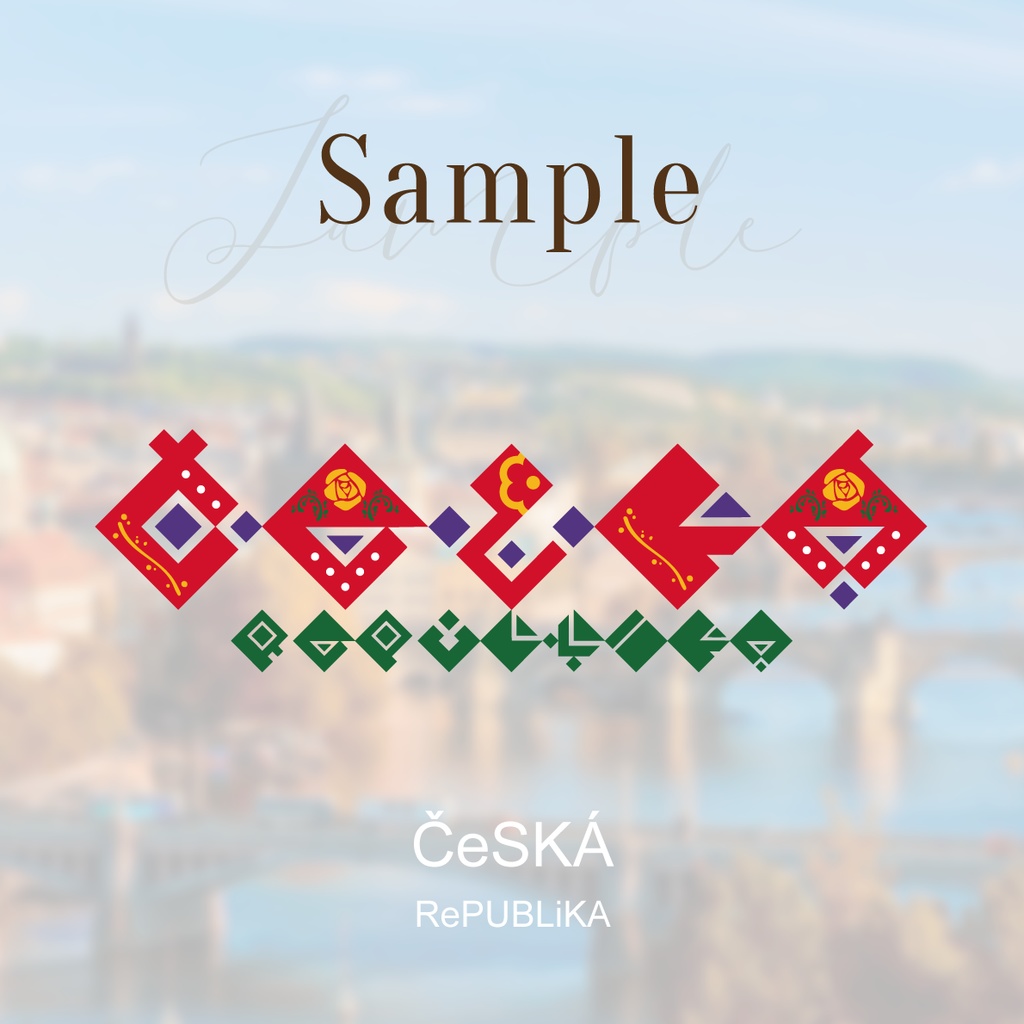
菱形のそれっぽい英字フォント
「なんか意味深な模様を置きたいけどなんも思いつかん!」という時の手助けになりそうな菱形英字フォントを作りました。中にサンプルのような模様などを適当に描いたりするとそれっぽさが増す...かも知れません。 【収録ファイル】 ◇Read Me(txt.) ◇フォント(otf. / ttf.) 英語アルファベット(大文字・小文字) ※サンプルの「Č」や「Á」のような文字が必要な場合は、上から要素を書き足すなど工夫してください。 【注意事項】 ◇いろいろ“甘い”です。お遊び程度にご利用ください。 ◇商用・非商用を問わず無料でご利用いただけるフリーフォントですが、著作権は放棄していません。 ◇無保証です。自己責任でご利用ください。 ◇予告なしにフォントデータを編集・改良などする可能性があります。 【禁止事項】 ◇フォントデータの改変・無断転載・再配布・販売(フォントそのものの改変などは禁止していません。ex.) Adobe Illustratorなどのソフトでフォントをアウトライン化し、編集する) ◇このフォントを利用した制作物(ロゴなど)の商標登録 ◇公序良俗に反する利用 常識の範囲内での利用をお願いしています。